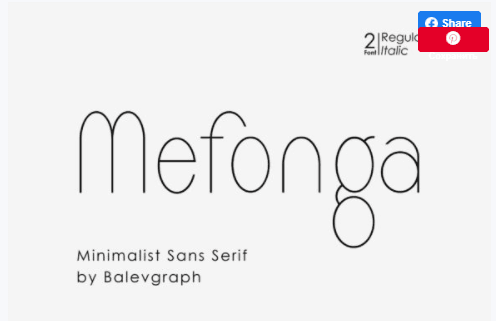
Mefonga Font
Mefonga - это тонкий и аккуратный шрифт без засечек. Этот адаптируемый шрифт отлично подойдет для самых разных дизайнерских идей. Это добавит веселья и дружелюбия каждому из ваших проектов!